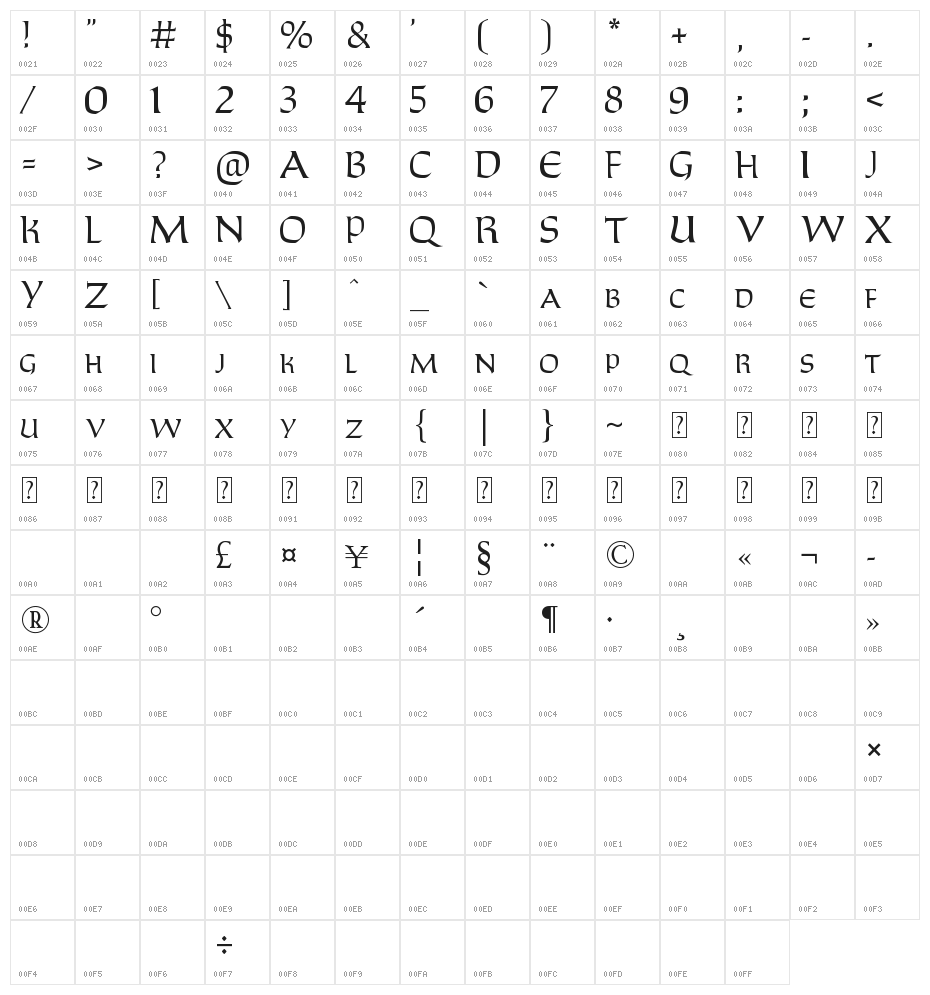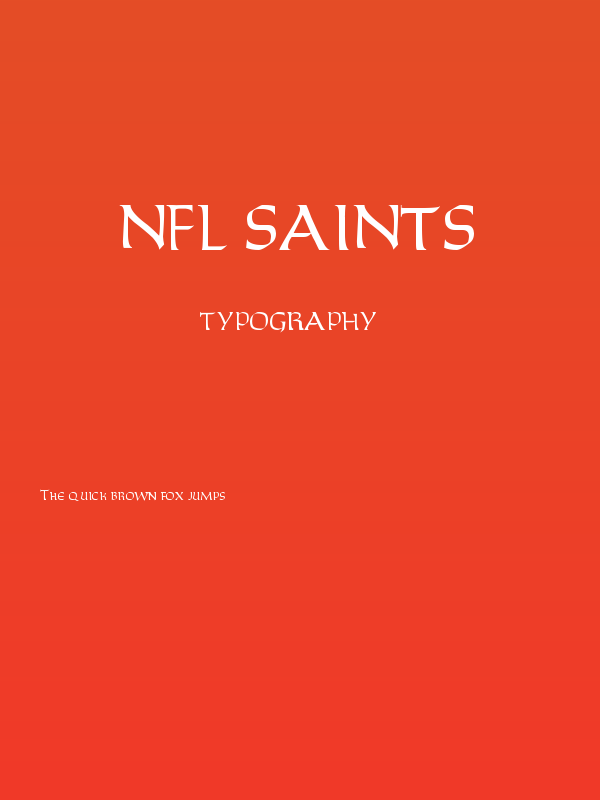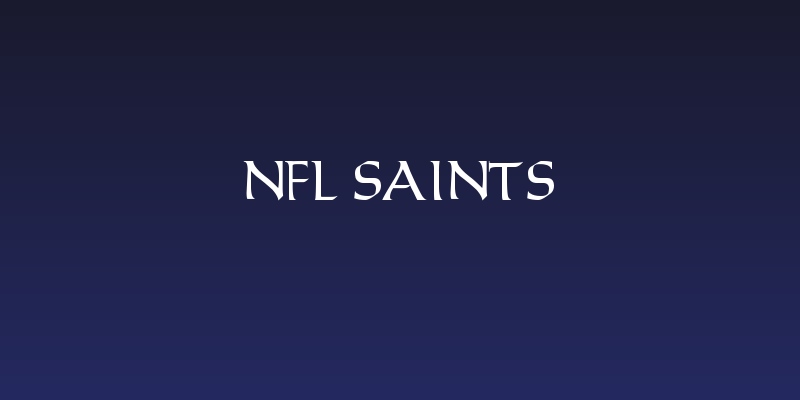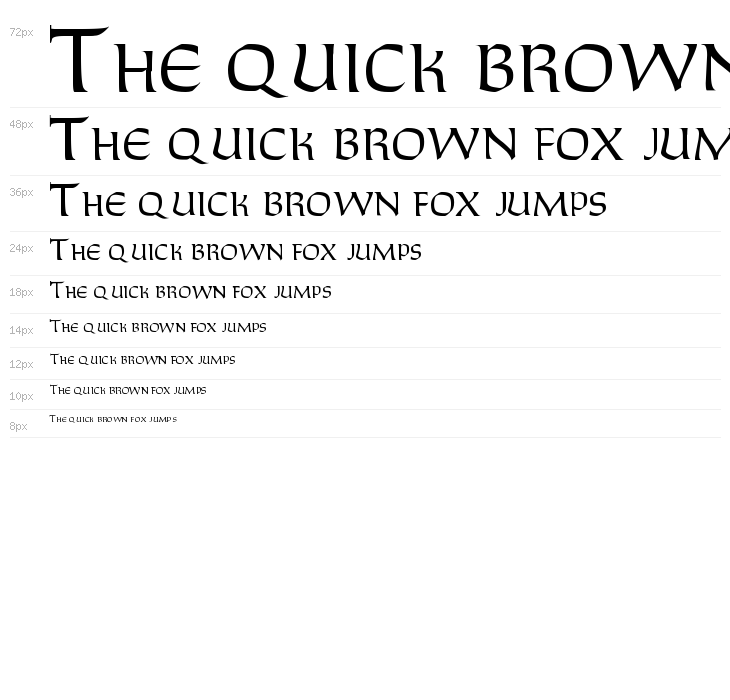
NFL Saints Font
| Stile generale | Modern, Vintage |
| Progetti proposti | Ideal for sports team branding, event posters, or any project requiring a strong, impactful typeface. |